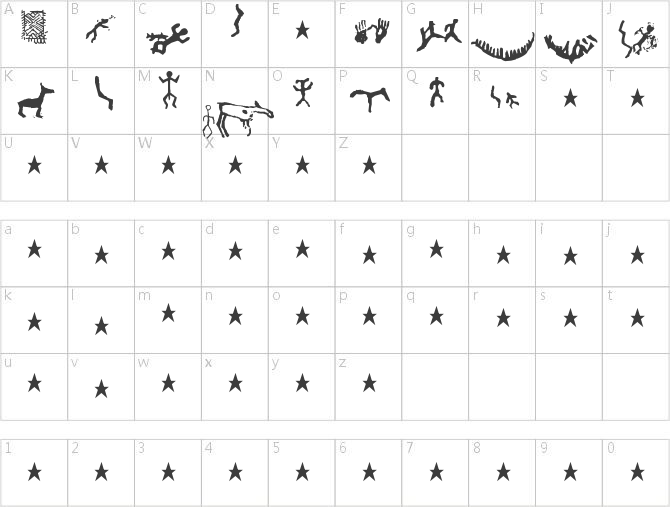
Finnish-Rock-Paintings 詳情頁
Finnish-Rock-Paintings字體字庫是一款讓人賞心悅目、百看不厭的英文字體,適合各類廣告和產(chǎn)品包裝設(shè)計應(yīng)用,字體大小0.01MB,格式為ttf字體,上傳用戶是15331803325,作者/版權(quán)方為未知